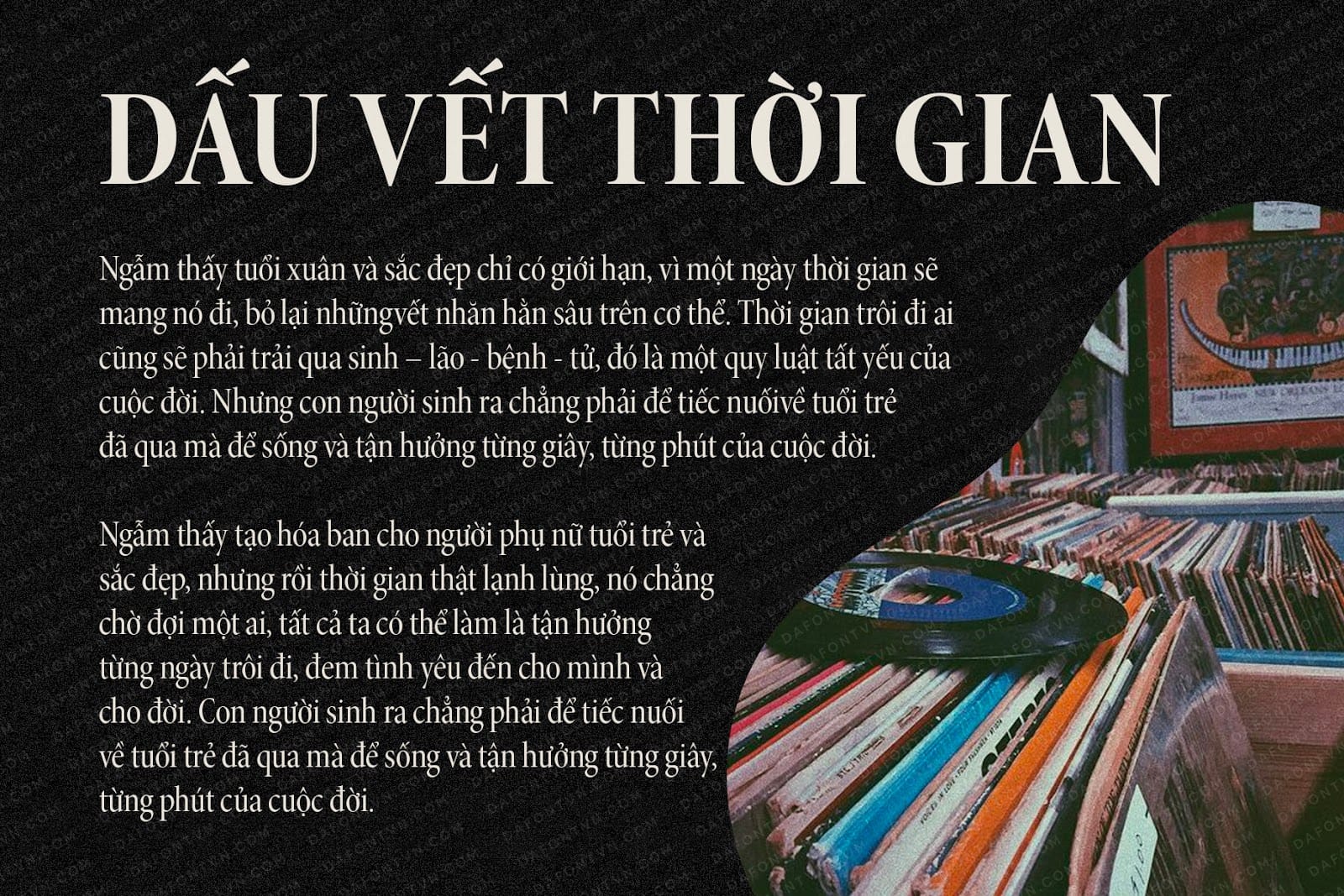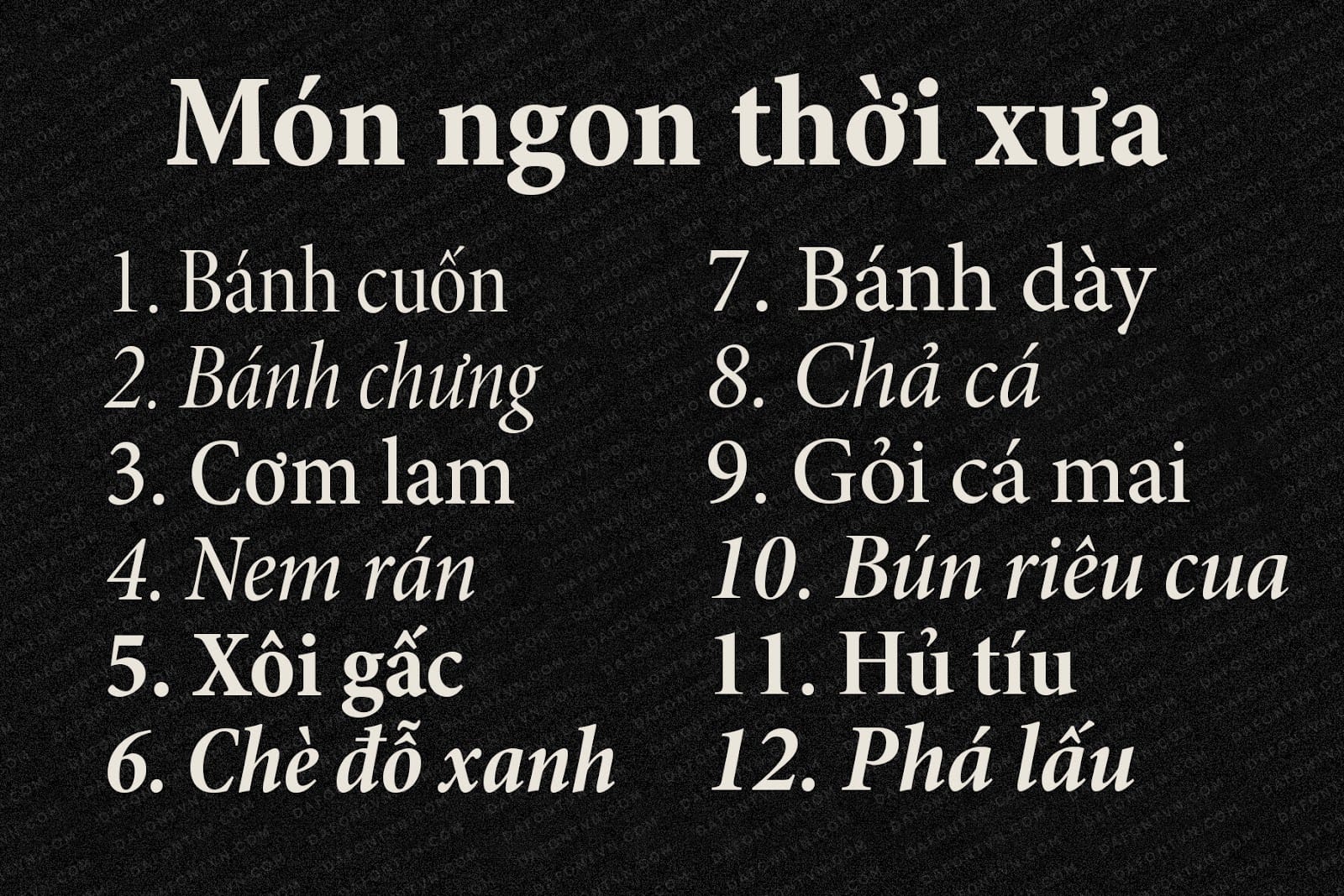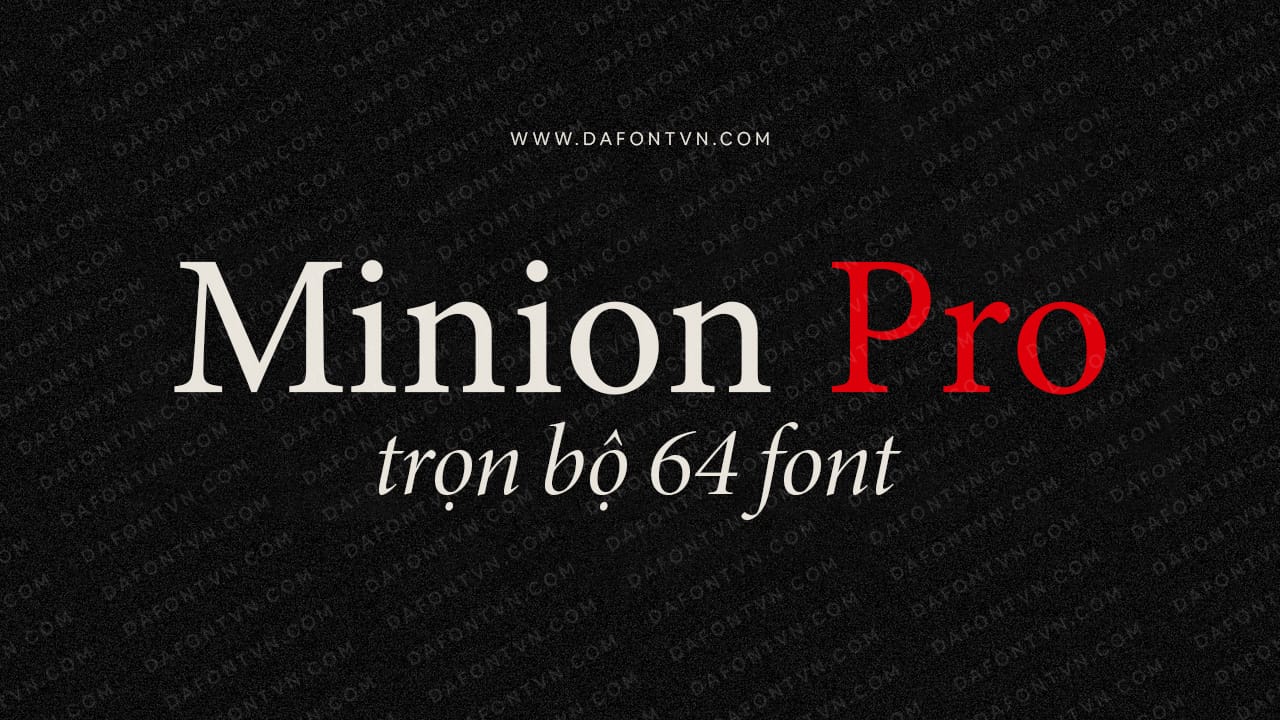
Minion Pro được phát hành lần đầu tiên vào năm 1990. Các bổ sung Cyrillic được phát hành vào năm 1992, và cuối cùng là phiên bản OpenType Pro được phát hành vào năm 2000.
Minion Pro được lấy cảm hứng từ các kiểu chữ cổ điển, vẻ đẹp vượt thời gian của những phông chữ cuối thời kỳ Phục hưng. Nó được tạo ra chủ yếu dưới dạng dạng phông chữ văn bản truyền thống nhưng thích ứng tốt với công nghệ kỹ thuật số ngày nay, thể hiện sự phong phú của các hình thức baroque trong các định dạng văn bản hiện đại.
Minion Pro kết hợp các đặc tính thẩm mỹ và chức năng giúp văn bản có khả năng đọc cao với tính linh hoạt và khả năng kiểm soát kiểu chữ chưa từng có, cho dù đối với các văn bản hiển thị hoặc văn bản dài.
Minion Pro Family có ba trọng lượng và hai chiều rộng, mỗi trọng lượng có các biến thể kích thước quang học và mỗi biến thể hỗ trợ đầy đủ các ngôn ngữ phương Tây, bao gồm cả tiếng Hy Lạp và tiếng Cyrillic. Với nhiều chữ ghép, chữ hoa nhỏ, hình vẽ kiểu cũ, dấu gạch ngang và các hình tượng được thêm vào, rõ ràng bộ font phù hợp với hầu hết mọi mục đích sử dụng.